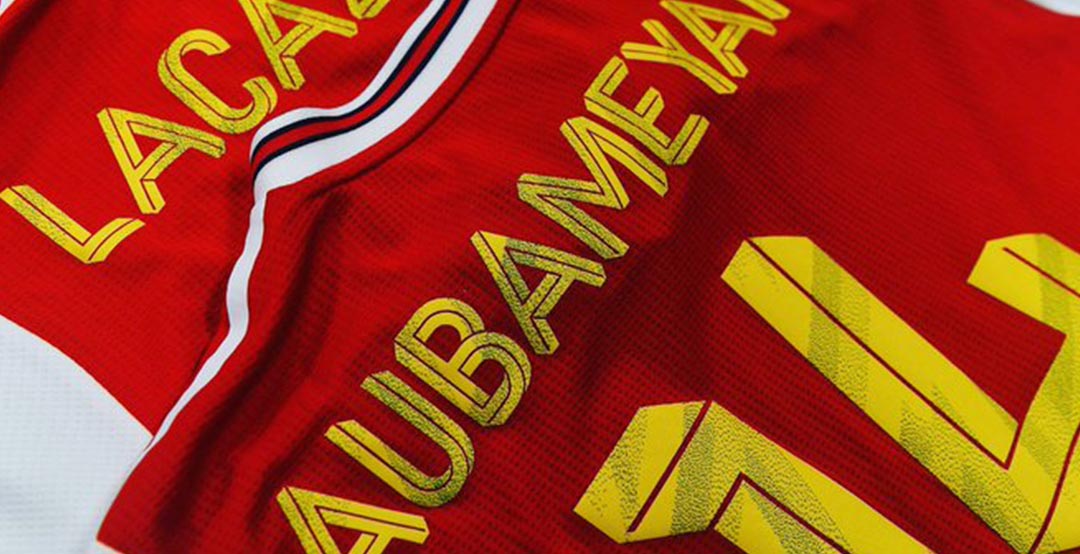
Arsenal Debütiert Adidas 19-20 Heimtrikot mit Einzigartiger "Bruised Banana"-Schriftart
Beim gestrigen 3:0-Sieg in der Saisonvorbereitung gegen die Colorado Rapids betraten die Arsenal-Spieler in ihrem neuen Adidas 2019-2020 Trikot erstmals das Spielfeld. Und während das Trikot vor einigen Tagen noch unverändert präsentiert wurde, verwendeten Arsenal und die Drei Streifen eine besondere Schriftart, die die Leute ins Gespräch brach.
Auf dem Platz | Adidas Arsenal 19-20 Home Jersey With Yellow Font
Arsenal und Adidas kombinierten das neue 2019-20 Trikot mit gelben Kaderzahlen, inspiriert von dem neuen "Bruised Banana"-Auswärtstrikot, das heute offiziell vorgestellt wurde. Die Zahlen und Buchstaben basieren auf der neuen Arsenal 2019-2020 Trikot-Schriftart, sind aber mit dem besondere nBruised-Banana-Muster und den Farben des Auswärtstrikots ausgestattet.
Leider oder zum Glück, wie auch immer du diese gelben Nummern auf dem Heimtrikot findest, war es ein einmaliges Ereignis, um das neue Arsenal 2019-2020 Auswärtstrikot zu bewerben und wird mit ziemlicher Sicherheit nie wieder zum Einsatz kommen.
Das Arsenal 2019-20 Trikot ist eine moderne Interpretation des legendären Bruised Banana Trikots der 90er Jahre.